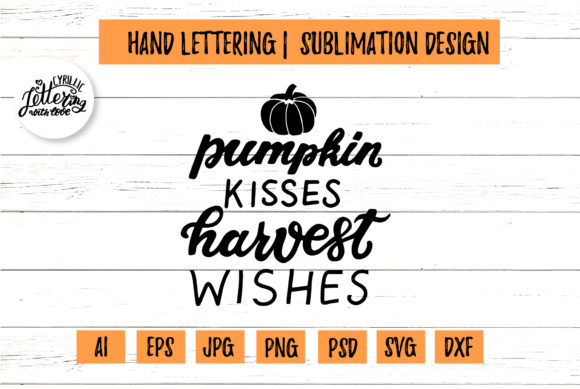
Pumpkin Kisses Harvest Wishes
Si buscas recursos de alta calidad como Pumpkin Kisses Harvest Wishes, este paquete premium es una opción fantástica para tus proyectos creativos.
Elaborado con precisión, Pumpkin Kisses Harvest Wishes proporciona vectores limpios, tipografía suave y una licencia comercial para tu tranquilidad.